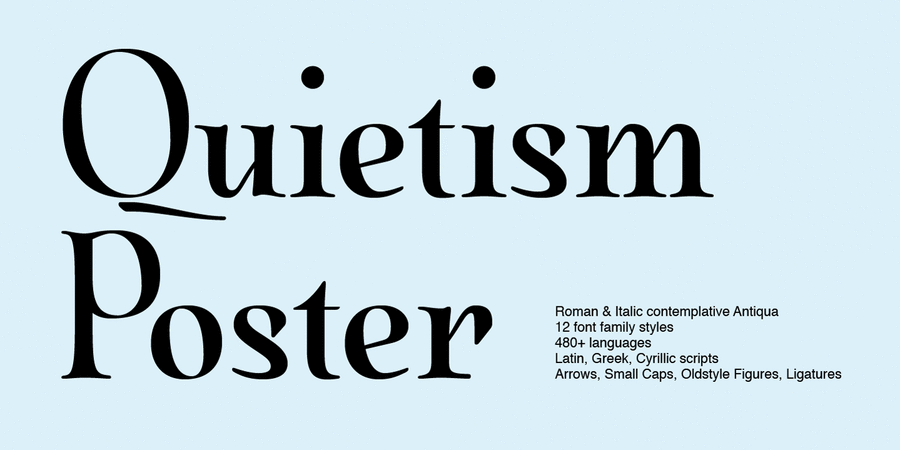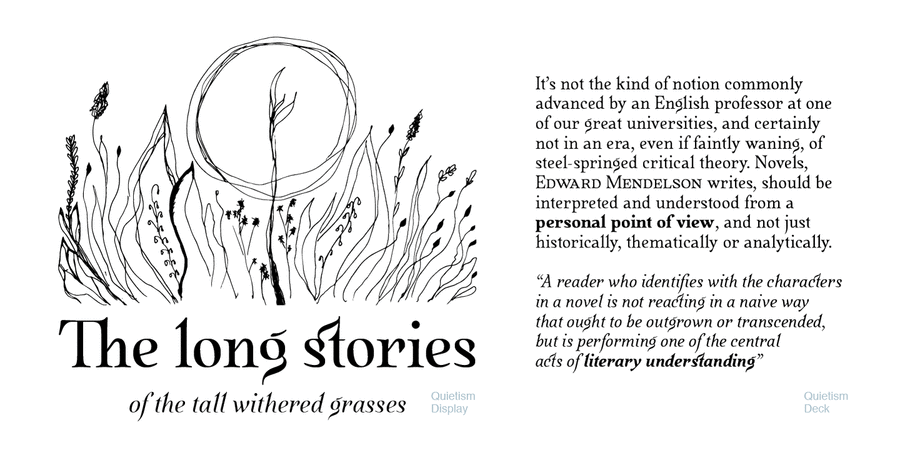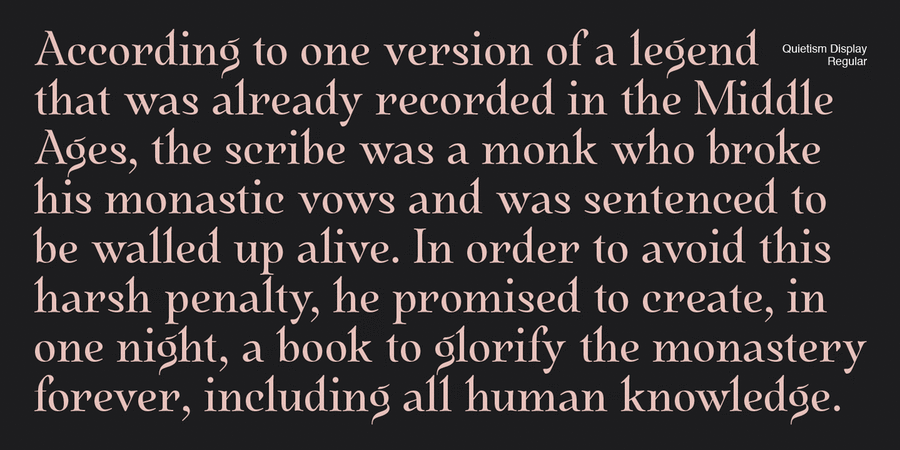
Опис гарнітури Quietism Poster – контрастна акцидентна підродина шрифтів для написів великого розміру.
Quietism – це м'яка споглядальна антиква зі спрямованими до неба верхніми виносними елементами, натхненна філософією квієтизму. Ясність розуму досягається за рахунок приведення тіла в стан спокою і споглядання, і це відображено в дизайні – м'які спокійні горизонтальні засічки (тіло) протиставлені гострим верхнім виносним елементам (розум). Особливостями дизайну є чотири підродини різних оптичних розмірів з різною висотою рядкових і контрастністю, діагональний стресс старого стилю, цифри старого стилю за замовчуванням, гладкі деталі та дещо затемну текстуру.
Накреслення: 42. Thin, Light, Regular, Medium, Bold, Black ваги. Прямі й курсивні накреслення. Оптичні розміри (підродини): Text, Deck, Display, Poster. Варіативні шрифти: Roman та Italic. Осі – Weight, Contrast, X-Height. Писемності: Latin, Greek, Cyrillic. Кількість мов: 480+. Кількість символів: 1845. Кернінг: 4553 класових пар. Хінтинг: Manual PostScript для статичних шрифтів. Формат: OTF – OpenType PostScript and TTF – OpenType with TrueType outlines for Variable fonts.
Функції OpenType:
Оптичний розмір: Шрифтова гарнітура представлена чотирма підродинами: Text (низький контраст, високий x-height – для параграфу 10-20 pt), Deck (середній контраст, середній x-height – для підзаголовків 20+ pt), Display (високий контраст, середній x-height – для заголовків 72+ pt), Poster (високий контраст, низький x-height – для великого розміру 120+ pt). Варіативний шрифт: Quietism Variable представлений окремими файлами Roman та Italic та має три осі: Weight (Thin–Black), Contrast (Low-High), та X-Height (Low-High). Варіативні шрифти надають більше можливостей ніж статичні шрифти та включають в себе тисячи стилів які можна регулювати слайдерами у графічному редакторі чи за допомогою таблиці стилів CSS у браузері. Поєднання різних варіативних осей надає вам додаткові стилі, не представлені статичними шрифтами. Small Caps: Малі літери замінюються на малі заглавні. Capitals to Small Caps: Великі літери, цифри та деякі розділові знаки замінюються малими заглавними. Case Sensitive Forms та стрілки вертикально вирівняні по великих літерах. Oldstyle figures замінюються на Lining figures. Oldstyle Figures: 0123456789 #%‰ використовуються за замовчуванням. Lining Figures: 0123456789 #%‰. Цифри тієї ж висоти що й великі літери (cap height). Proportional Figures: Lining, Oldstyle, Small Caps, Capitals та Small Caps. Tabular Figures: Lining, Oldstyle, Small Caps, Capitals та Small Caps. Ordinals: adehnorst. Superscript, Subscript, Numerator, Denominator: 0123456789. Fractions: ¼½¾⅐⅑⅒⅓⅔⅕⅖⅗⅘⅙⅚⅛⅜⅝⅞⅟ Прекомпоновані. Будь-які інші комбінації "число+слеш+число" автоматично замінюється на "Numerator+fraction+Denominator". Slashed Zero: Усі цифри 0 замінюються на нуль із рискою. Contextual Alternates: Символ нумеріції (#) перед великими літерами замінюється на його версію що вертикально відцентрована з великими літерами. Символ дефісу (-) між двома великими літерами замінюється на його версію, що вертикально відцентрована з великими літерами. Перша літера T у комбінації TT замінюється на її альтернативну версію. Літери vwy перед літерами fijmnprtuvwxy замінюються на їх альтернативні версії щоб створювати кращу текстуру тексту. Contextual Alternates (Greek): ΆΈΉΊΌΎΏ. Грецькі великі літери у режимах All Caps та Small Caps втрачають акцент tonos (але залишають акцент dieresis). Увімкнено за замовчуванням. Stylistic Alternates: FTГТИЦЩцщ та їх версії з діакритичними знаками. Stylistic Set 01 “Arrows”: Вліво <- Вправо -> Угору <| Вниз |> Вліво вправо <-> Угору вниз <|> Вліво вгору <\ Вправо вгору /> Вліво вниз Вправо вниз \>. Stylistic Set 02 “Round-Square Cyrillic”: Літери ДИЙЍЛФвгджзийѝклнптцчшщьъю замінюються на їх болгарську чи російську кирилічну форму. Stylistic Set 03 “Cyrillic Tse Shcha short tails”: Літери ЦЩцщ замінюються на їх альтернативну форму з коротким хвостом. Stylistic Set 04 “Cyrillic I full serifs”: Літери ИЙЍӢ замінюються на їх альтернативну форму з внутрішніми засічками. Stylistic Set 05 “FT bent inward serif”: Літери FTГ та їх версії з діакритичними знаками замінюються на їх альтернативну версію, у якій права верхня засічка завернута всередину. Stylistic Set 06 “Small Caps centered on Capitals”: Small Caps вертикально відцентровані по великих літерах. Standard Ligatures: fi fl fb ff fh fj fk ffb ffh ffi ffj ffk ffl. Discretionary Ligatures: Th ct st. Localized Forms: 52 символи автоматично змінюють свій вигляд для наступних мов – Azeri, Bulgarian, Catalan, Dutch, German, Kazakh, Macedonian, Moldavian, Polish, Romanian, Serbian, Tatar, Turkish. Glyph Composition/Decomposition (Версії літер з діакритичними знаками): Повний набір латинських та базовий набір в'єтнамських літер із діакритичними знаками (571 символ) прекомпоновані.
Шрифт розробив Михайло Рафайлик у 2022 році.
Асоціації з сімейством шрифтів Quietism PosterОсобистість і характер гарнітури:
тонкий, легкий, культурний, освічений, гуманітарний, крихкий, благородний, якісний, вишуканий, художній, гострий, ювелірний, худий, гнучкий, пластичний, динамічний, живий, ремісничий, старомодний, історичний, старовинний, дивний, крафтовий, джентльменський, красивий, зразковий, ввічливий, елегантний, граціозний, ритмічний, прекрасний, виразний, майстерний, аристократичний, акуратний, музичний, витончений, естетичний, добірний, сріблястий, поетичний, натхненний, весільний, жіночний, делікатний, поважний, старанний, гармонійний, комільфо, пафосний, дорогий, розкішний, багатий, консервативний, традиційний, класичний, оповідний, дорогоцінний, урочистий, салонний, театральний, мінливий, чарівний, магічний, містичний, манірний, драматичний, яскравий, самобутній, химерний, демонстративний, артистичний, естетський, оригінальний, характерний, претензійний, екстравагантний, нонконформістський, богемний, ностальгічний, олдскульний, активний, дзвінкий, святковий, легендарний, казковий, гордий, фантастичний, сексуальний, романтичний, лісовий, тактичний, елітний, глянцевий, блискучий, гламурний, ефектний, пристрасний, гарненький, знаменитий, ошатний, мотивуючий, щільний, тісний, сильний, помітний, експериментальний, амбітний, важкий, епатажний
мода, срібло, живопис, художник, гравірування, весілля, культура, філософія, симфонія, парфумерія, музей, комільфо, мистецтво, преміум, геральдика, бібліотека, література, естетика, поезія, музика, вино, замок, концерт, обід, вечеря, ювелір, коштовності, ресторан, парфуми, пейзаж, одяг, театр, антикваріат, епос, меморіал, пам'ятник, прикраса, надгробок, історія, ремесло, готель, казка, Чарівна казка, карти, гра, чай, свято, банкнота, легенда, цінні папери, Трофей, нагорода, кохання, романтика, розкіш, перукарня, бутік, тату, татуювання, балет, сукня, краса, виставка, люкс, драма, вечір, взуття, захід сонця, магія Гарнітура асоціюється з віком: